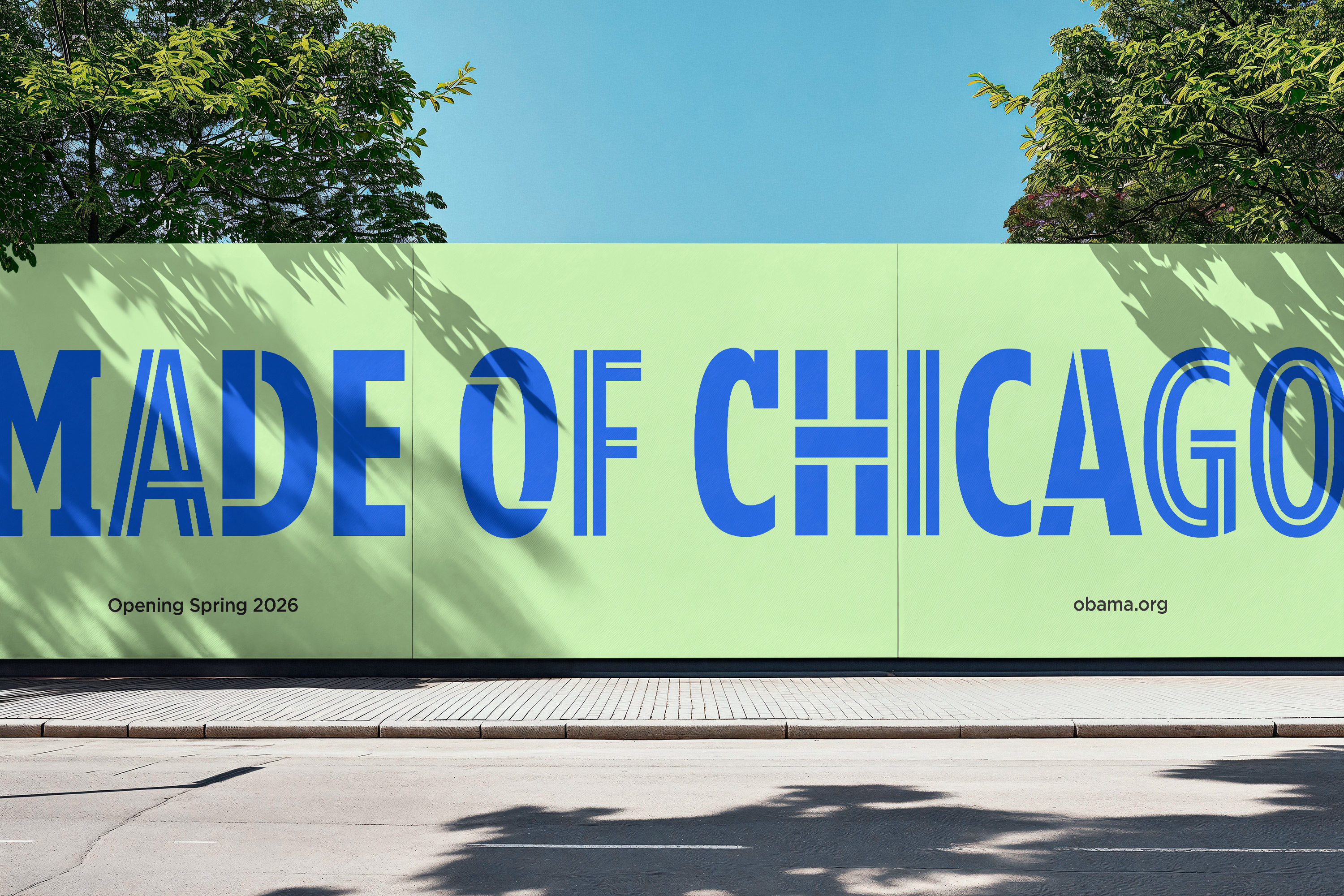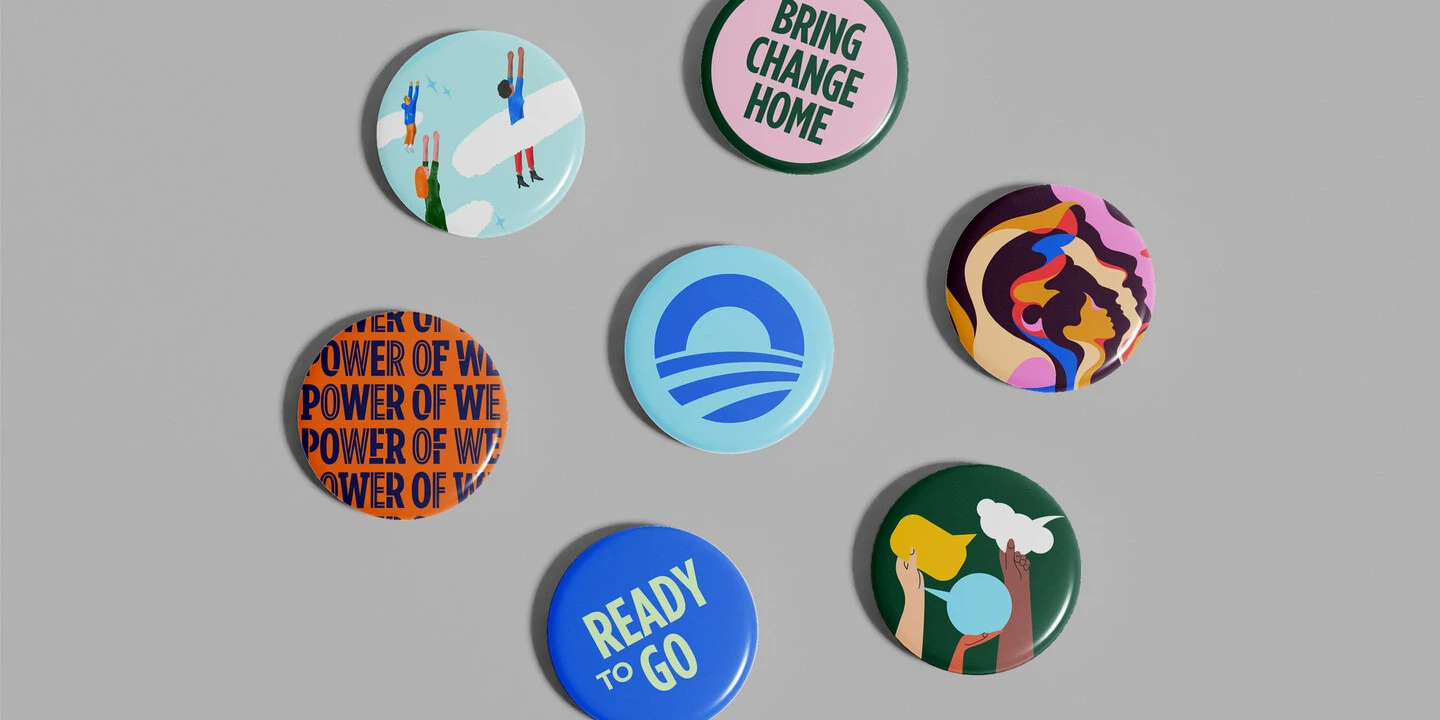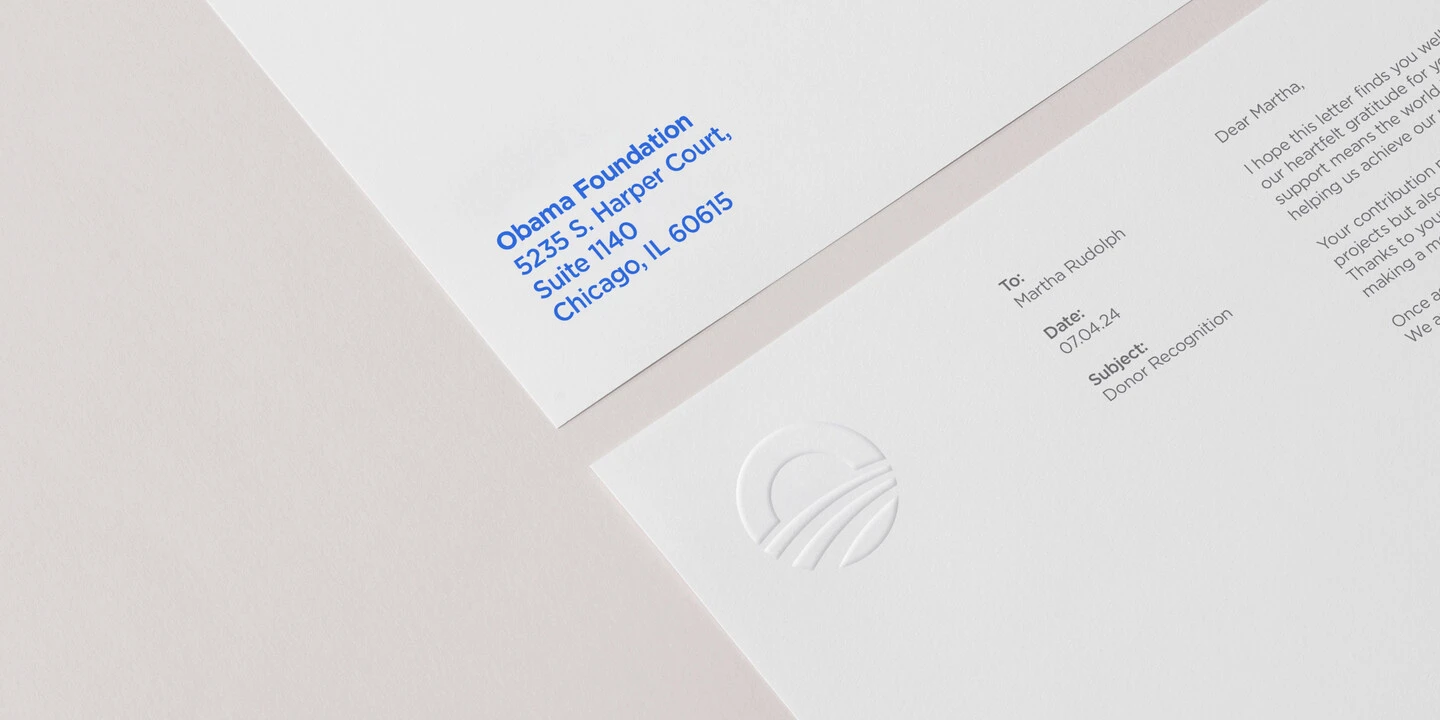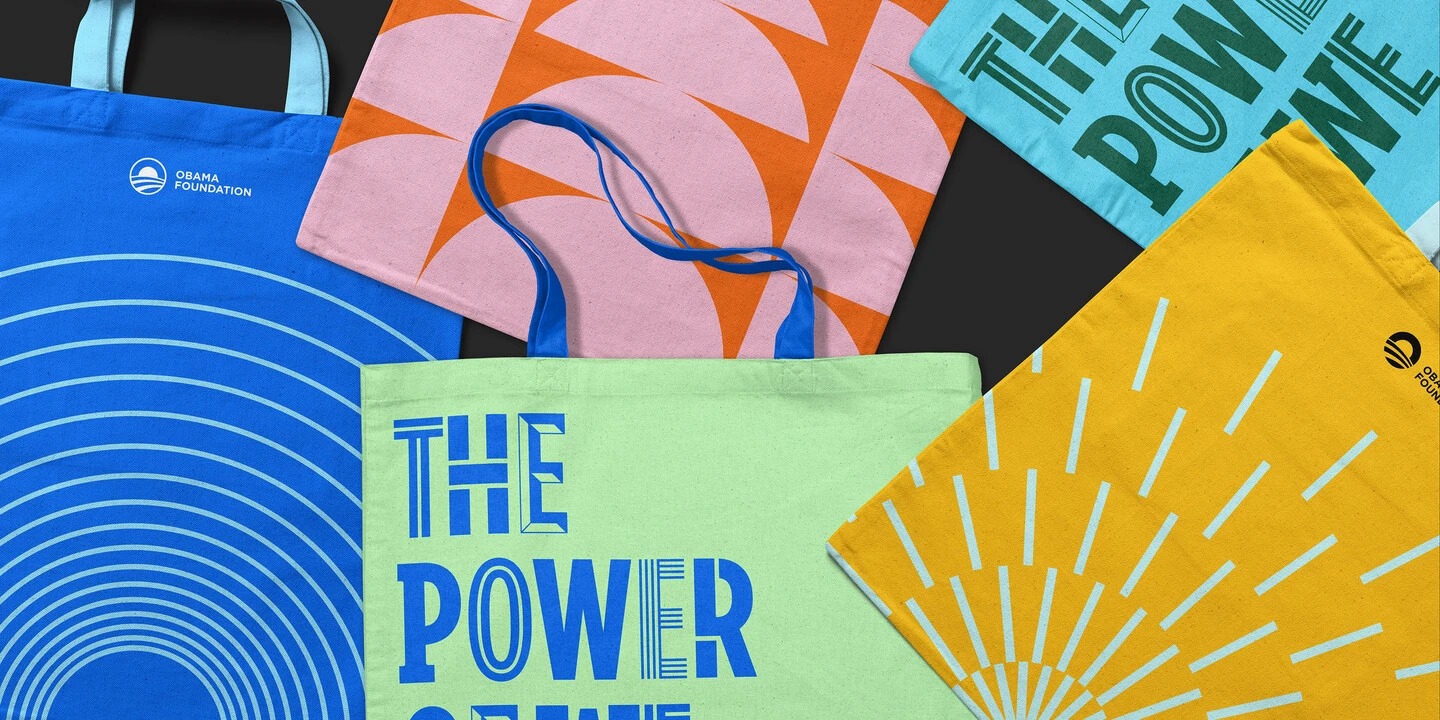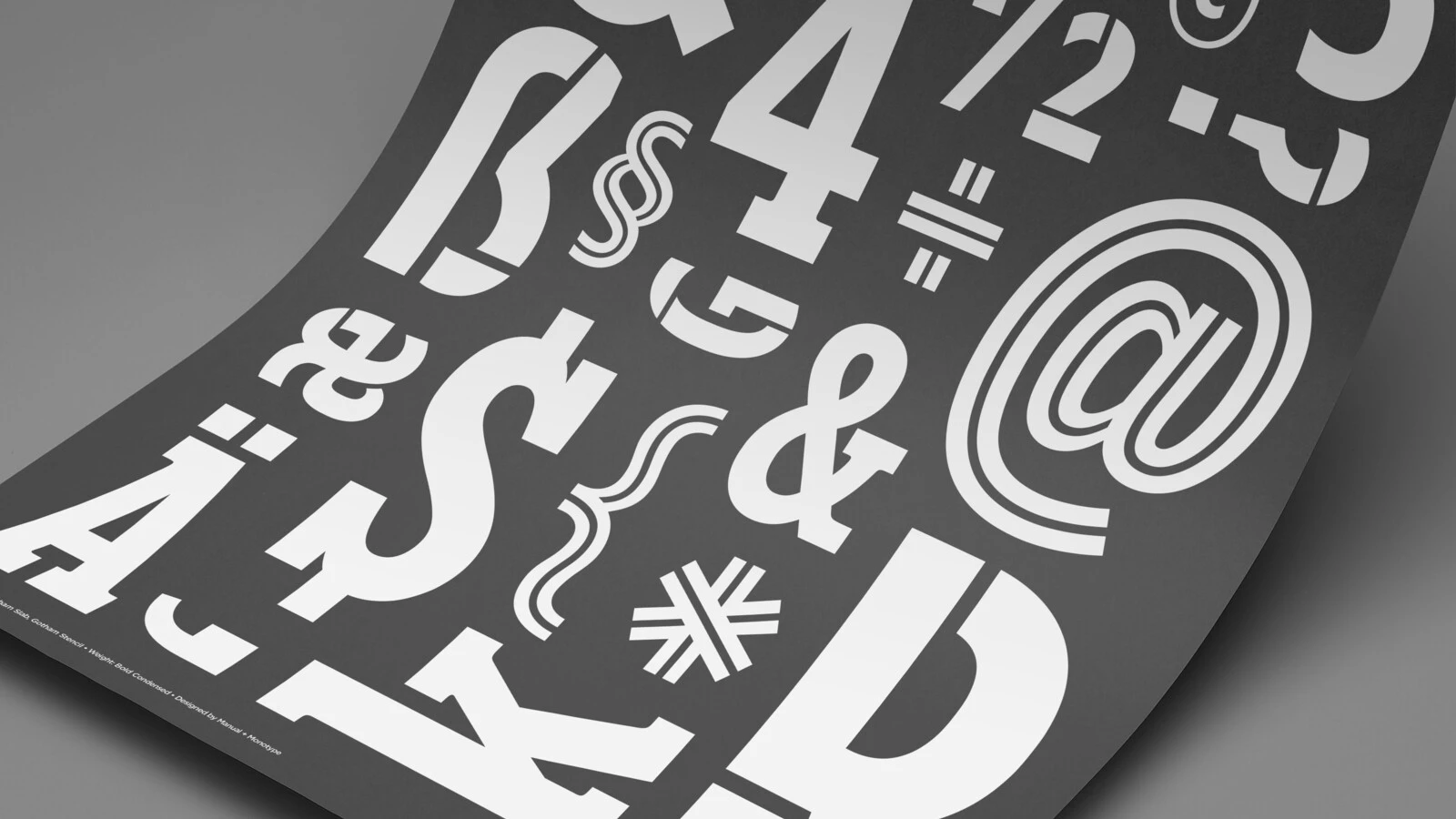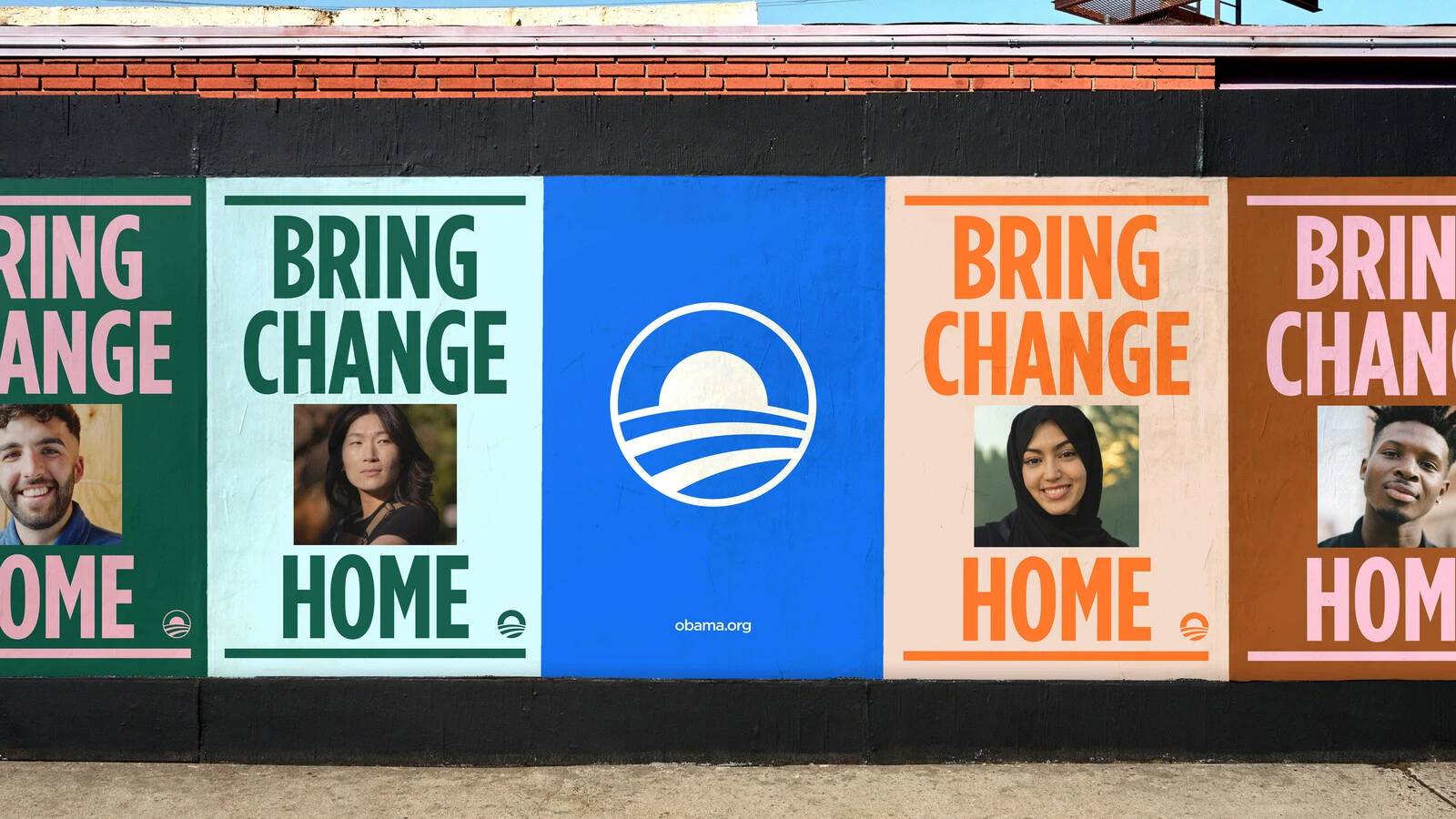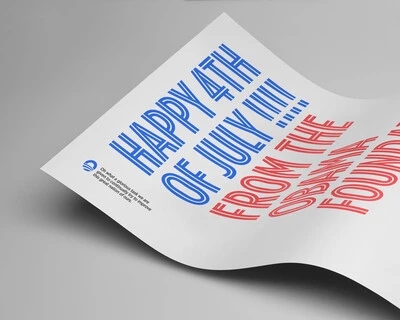
Le prochain chapitre de Gotham.
Comment Monotype a contribué à faire évoluer une police emblématique pour la  Fondation Obama.
Une police qui a marqué un mouvement.
Peu de polices sont aussi intimement liées à un moment culturel que Gotham. Lorsque Gotham Bold a été choisie comme police principale de la campagne Obama for America en 2007, elle devint synonyme du message de la campagne : espoir et changement. Ses formes marquées, ouvertes et rigoureuses reflétaient la personnalité du candidat et trouvèrent un écho auprès de millions de personnes. Aujourd’hui, alors que la Fondation Obama évolue, son identité de marque évolue elle aussi, ajoutant un nouveau chapitre à la riche histoire de Gotham.
Gotham Bold devint la représentation visuelle d’une campagne qui redéfinissait le branding politique. Sa simplicité géométrique dissimulait une structure optique sophistiquée, créant un équilibre entre clarté et accessibilité. Cet équilibre en fit le choix naturel pour la Fondation Obama, qui continua à utiliser Gotham dans les initiatives du président Obama après son mandat.
Alors que la Fondation élargissait ses programmes et se préparait à l’ouverture de l’Obama Presidential Center, il devint clair que la typographie devait suivre le rythme de sa mission grandissante. Le défi : faire évoluer Gotham sans perdre son essence, tout en y insufflant une nouvelle énergie et davantage de flexibilité.
Une vision pour une identité moderne.
Afin de développer une identité de marque renouvelée, la Fondation a collaboré avec son agence partenaire Manual Creative, qui conçut une stratégie incluant des versions sur mesure de Gotham adaptées à différents contextes et programmes. L’objectif était d’élargir la voix de Gotham et de créer pour chaque facette du travail de la Fondation une personnalité propre mais reliée aux autres. Le résultat a été une réorientation vers Gotham Condensed Bold comme style de police principal, complété par trois variantes sur mesure conçues pour des messages spécifiques :
• Gotham Inline : un style vivant et énergique, utilisé dans les communications liées au sport et aux univers sportifs.
• Gotham Slab Serif : un hommage à l’Americana historique, renforçant les thèmes de démocratie, d’éducation et d’engagement civique.
• Gotham Stencil : une interprétation contemporaine de l’esthétique des pochoirs, symbolisant l’engagement communautaire et la durabilité.
Chacun de ces nouveaux styles permet à la Fondation Obama de communiquer avec clarté et  efficacité, tout en maintenant une identité de marque cohérente.
L’art de la personnalisation.
La contribution de Monotype est allée bien au-delà de la simple exécution : Manual Creative et Monotype ont travaillé en véritable partenariat, combinant la vision créative de l’agence avec la précision typographique de Monotype. Sara Soskolne, typographe chez Monotype et impliquée depuis 2005 dans chaque extension de Gotham, a apporté sa compréhension profonde de l’ADN de la police au projet.
Si chaque variante présentait des défis de conception uniques, les versions Inline et Stencil se sont avérées particulièrement complexes. La structure condensée caractéristique a nécessité des ajustements visuels minutieux afin de garantir l’équilibre et la lisibilité. Le style Inline dut être repensé en cours de processus pour éviter des chevauchements indésirables, tandis que la variante Stencil a nécessité une approche organique et non conventionnelle plutôt qu’un schéma rigide.
Malgré ces défis, le processus s’est déroulé sans accroc. « Plus fluide que prévu », a déclaré Tom Crabtree, directeur créatif chez Manual. L’expertise de Monotype en matière de développement et de personnalisation de polices permit à chaque adaptation de préserver l’intégrité de Gotham tout en répondant aux besoins spécifiques de la Fondation.
Une police – et une marque – tournées vers l’avenir.
L’Obama Presidential Center regarde vers l’avenir : il a pour vocation d’inspirer et de renforcer la prochaine génération de leaders. Sa typographie porte cette vision – dynamique, puissante et indissociable de la mission de la Fondation.
Avec l’élargissement du répertoire Gotham, la Fondation dispose désormais d’un système typographique capable de soutenir ses programmes en expansion, tout en restant fidèle à l’identité qui avait autrefois enthousiasmé le public. La collaboration entre Manual Creative et Monotype a permis de garantir que chaque nouvelle variante de Gotham soit conçue avec soin, alliant histoire et innovation.
Alors que la Fondation Obama poursuit son travail essentiel, sa typographie continuera de jouer un rôle central dans sa communication, comme elle l’a toujours fait depuis le premier jour.